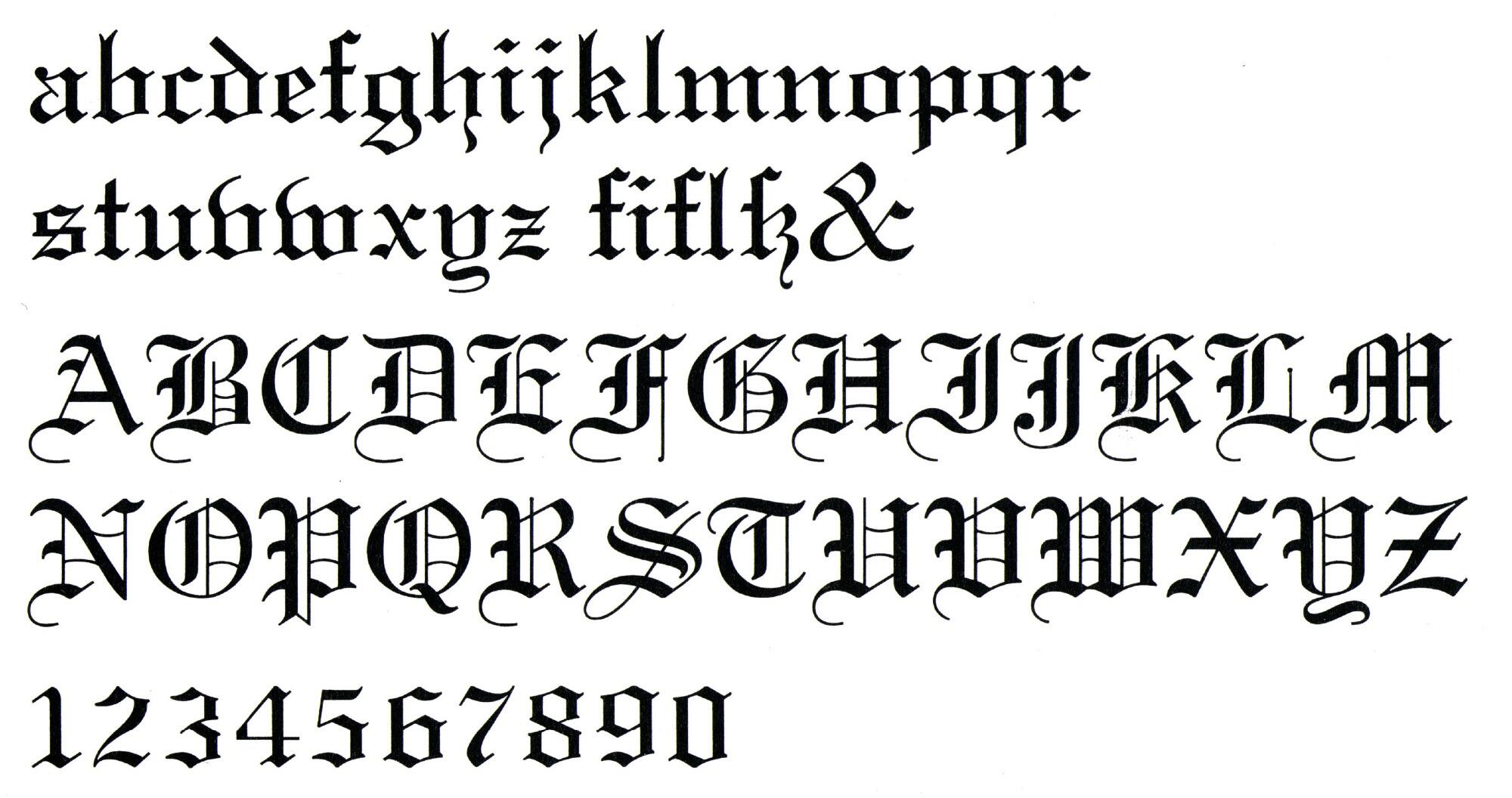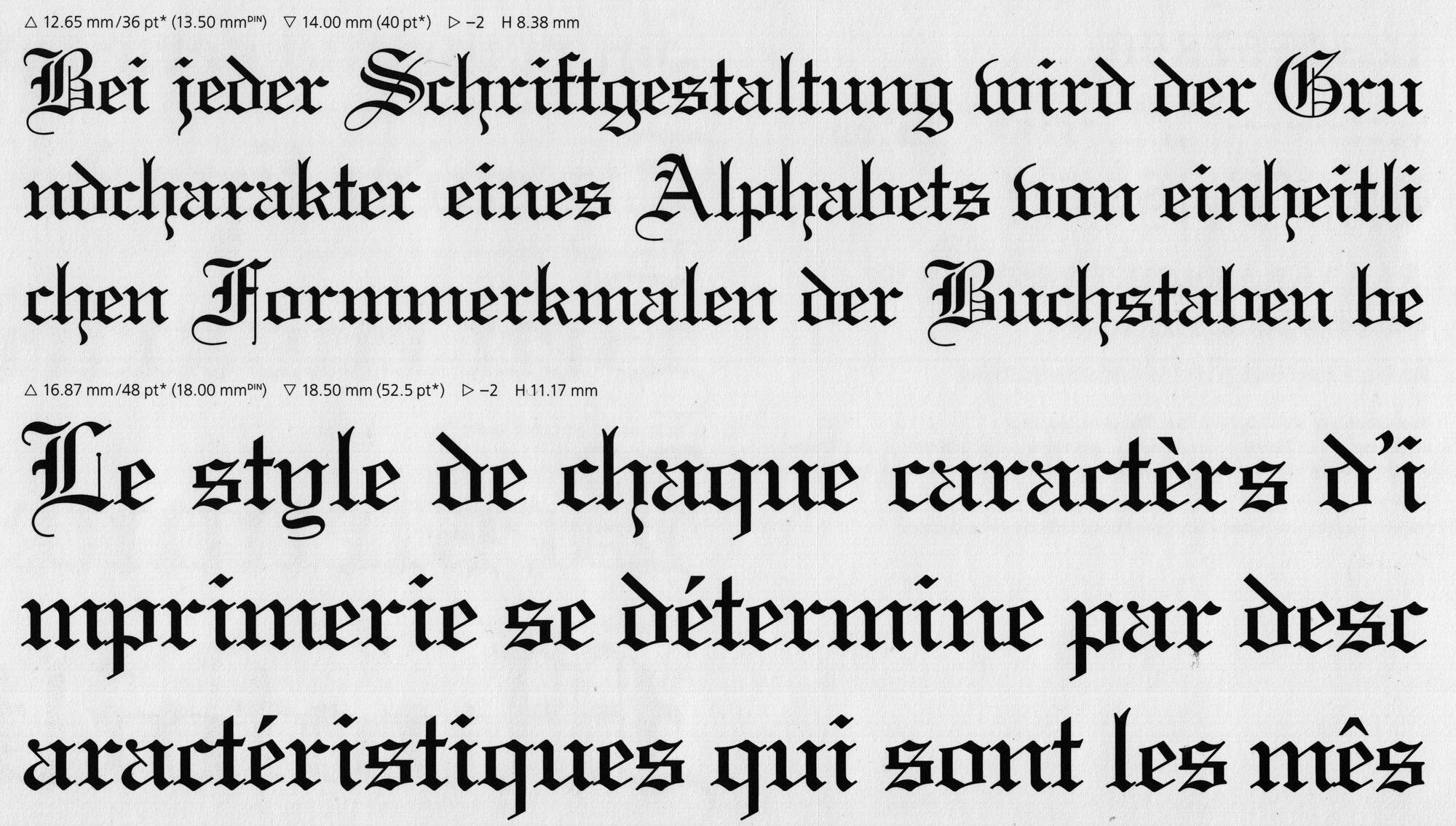
Diese relativ breit laufende, gotische Schrift wurde von Morris Fuller Benton entworfen und erschien Anfang des 20. Jahrhunderts bei American Type Founders. Die Schrift wurde international von verschiedenen Anbietern übernommen und und erschien für Linotype-Maschinen als Linotext. Die Schrift wurde später auch für den Foto- und Digitalsatz übernommen und ist weiterhin unter der Marke Linotype erhältlich.